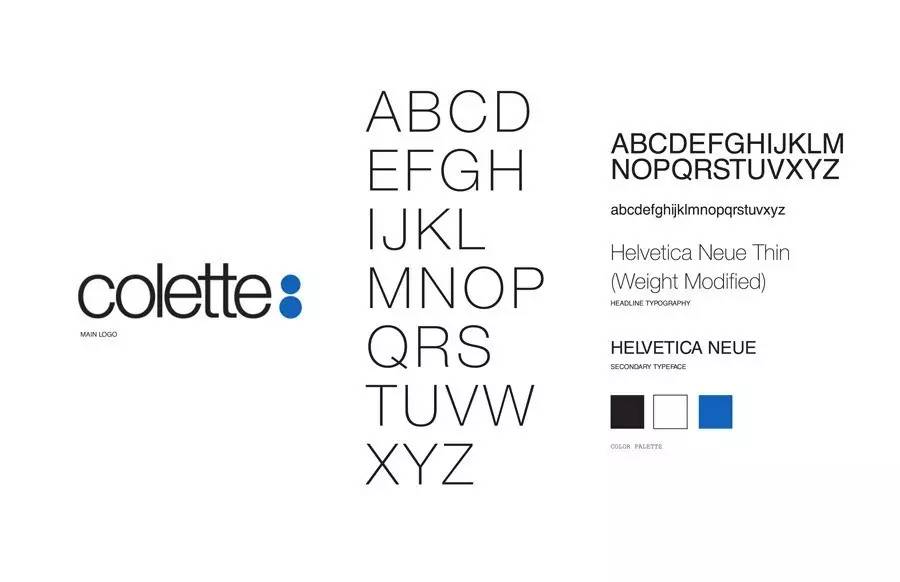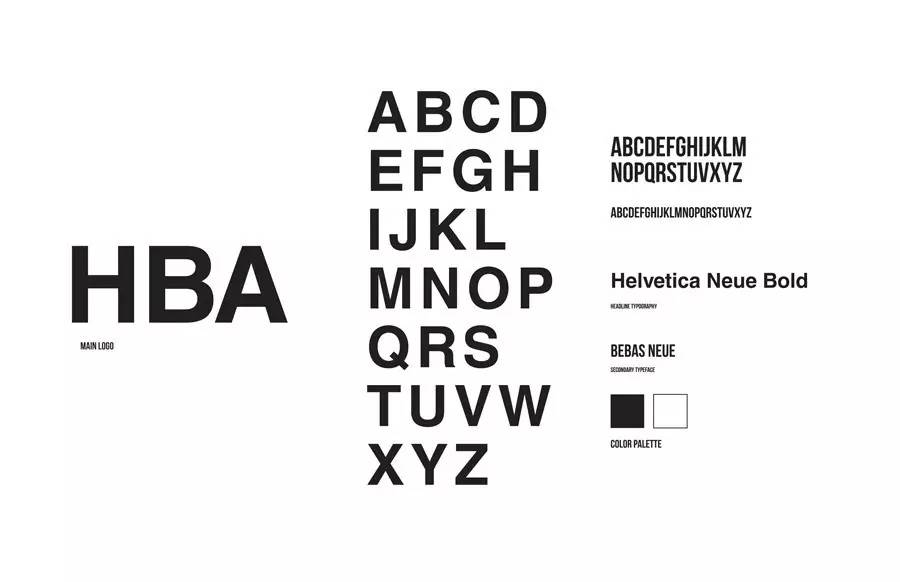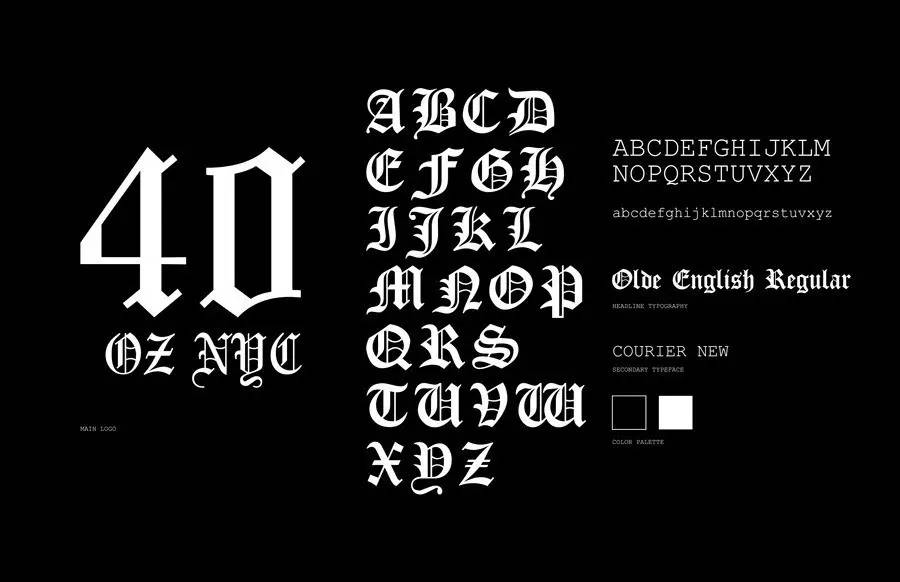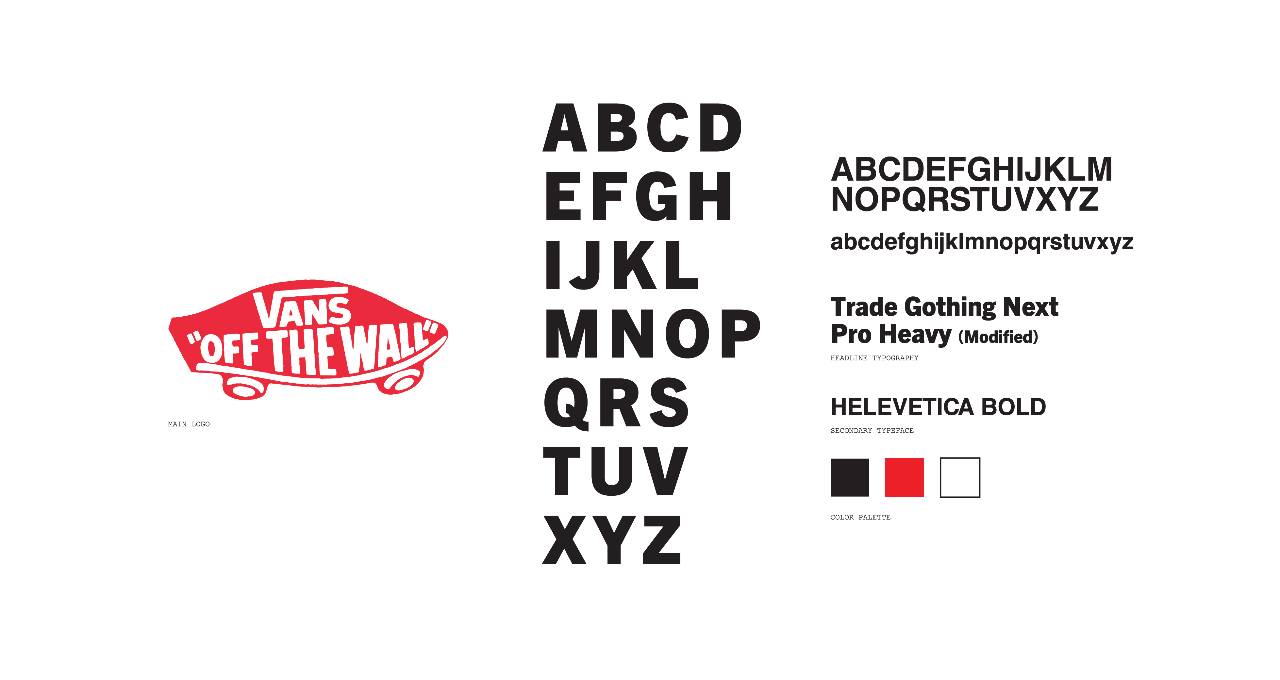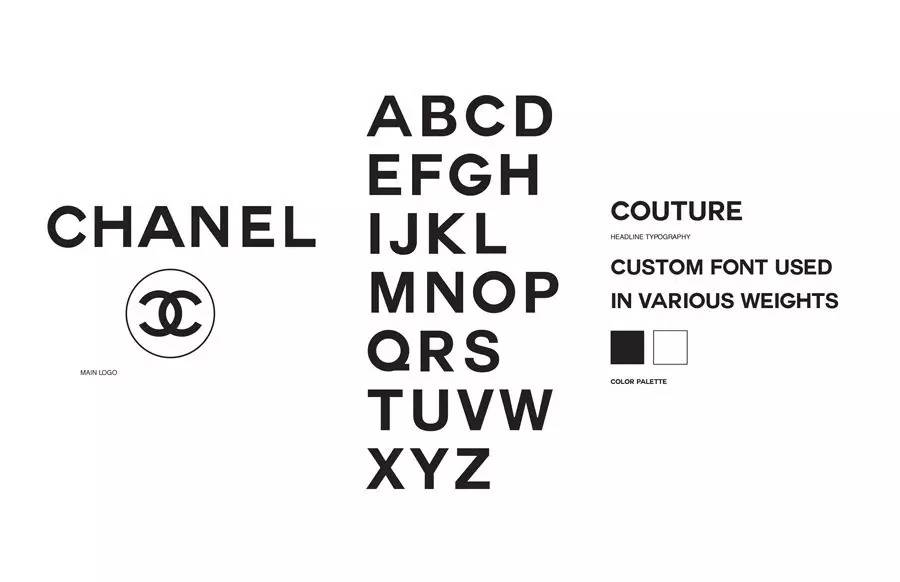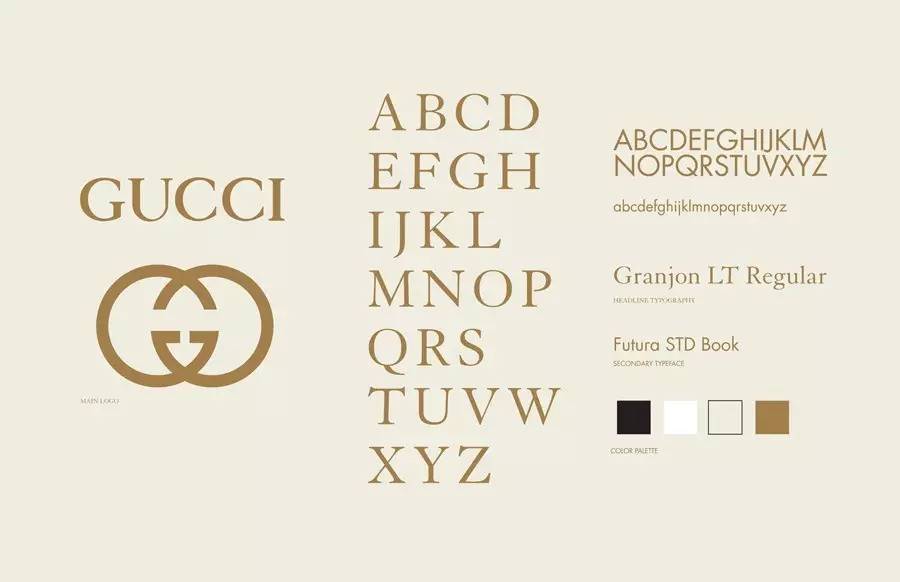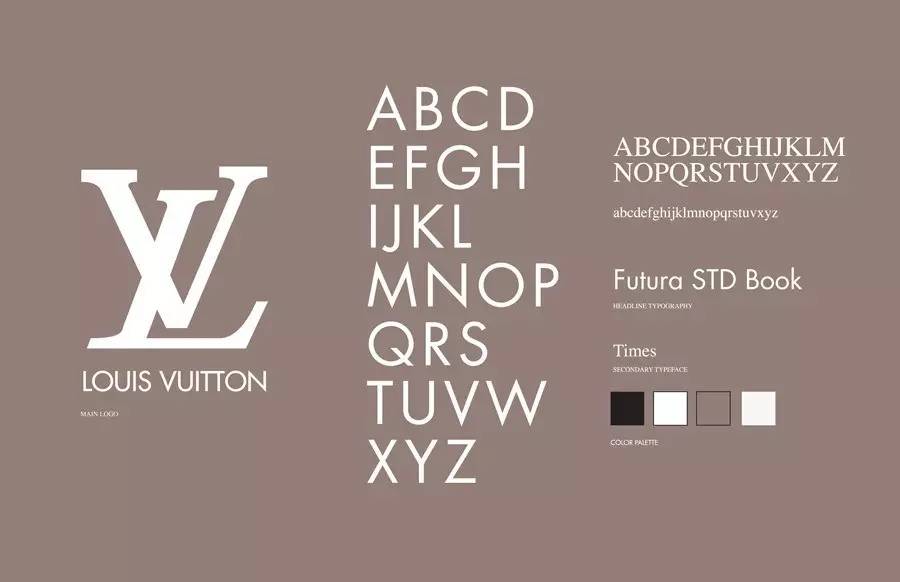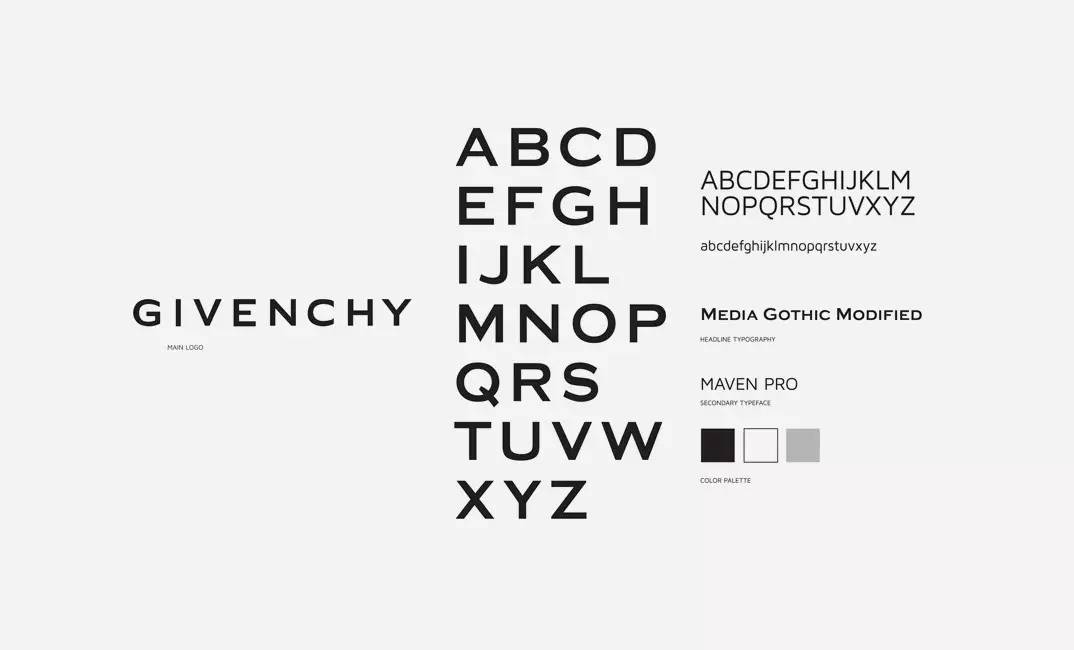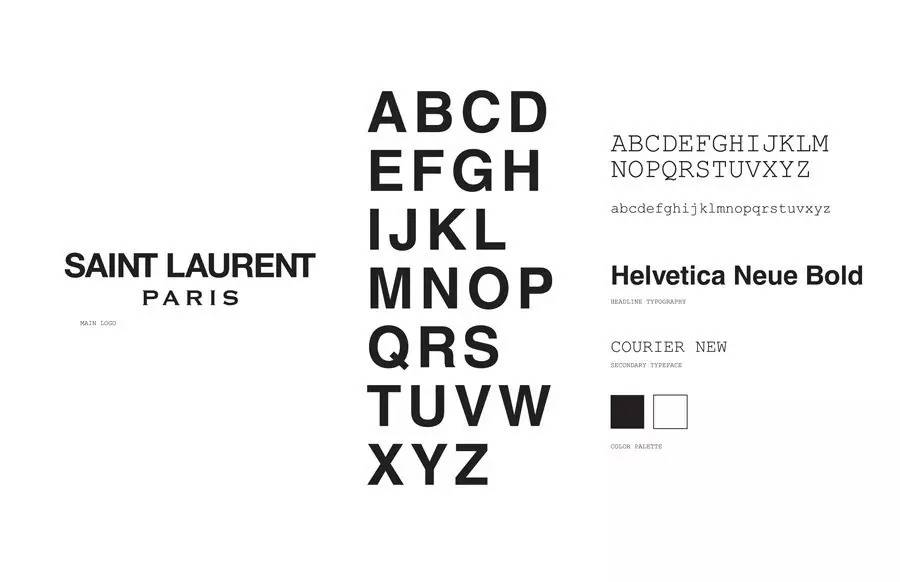
字体设计案例,24个时尚品牌的LOGO字体研究
潮流时尚网站SLAMXHYPE对24个时尚品牌的LOGO字体进行了研究,包括:adidas/Nike/GIVENCHY/LV/GUCCI/CHANEL/Timberland/Prada/Supreme/Saint Laurent/HBA/Visvim等。虽然这些潮牌们不停推出新品诱惑大家的钱,但是从LOGO字体来看大都以“Futura”和“Helvetica”为主。这两大字型的特点:形象干净、鲜明、丰富,既符合广告设计的一般需要,也吻合时尚品牌的形象要求。
Trend in the fashion website SLAMXHYPE 24 fashion brand LOGO fonts are studied, including: adidas, Nike, GIVENCHY, LV, GUCCI, CHANEL, Timberland, Prada, forceful, Saint Laurent, HBA, Visvim, etc. Although these popular LOGO are constantly introducing new temptation you money, but look from the LOGO font are given priority to with "severe" and "Helvetica". The characteristics of these two type: clean, bright image, rich, both comply with the general need of advertisement design, also fit the fashion brand image requirements.
Adidas
Chanel
Gucci
Louis Vuitton
Givenchy
SAINT LAURENT
NIKE
COMME des GARCONS
SUPREME
COLETTE
HBA
40OZ NYC
PRADA
Maison Martin Margiela
EN NOIR
APE BABY
A.P.C.
VANS
Timberland
VISVIM